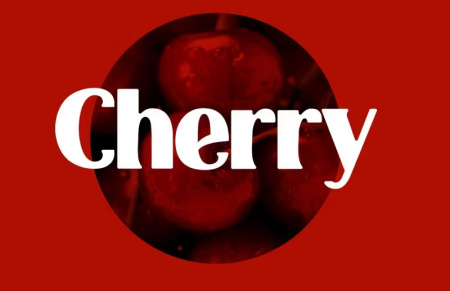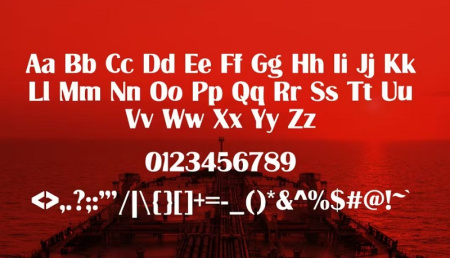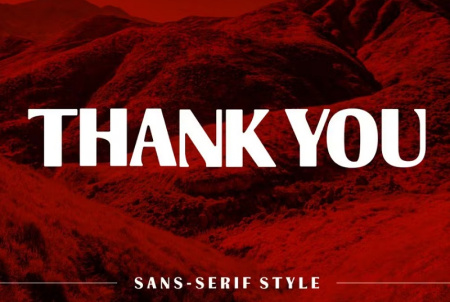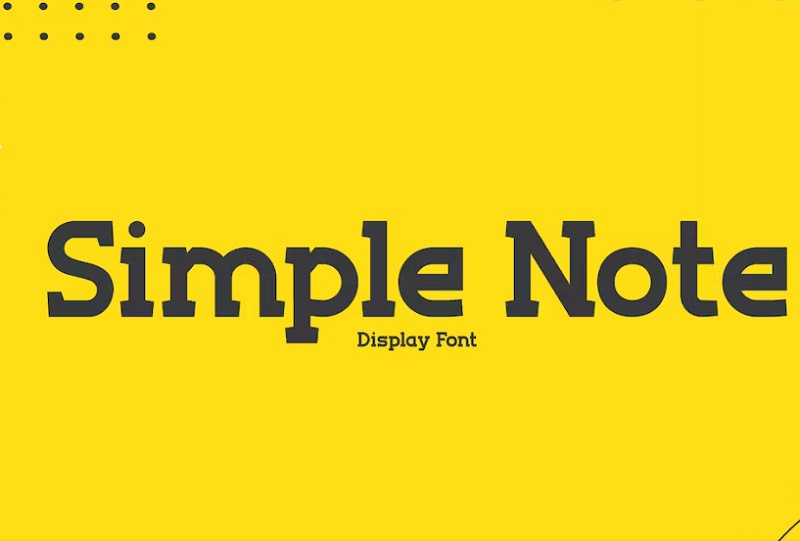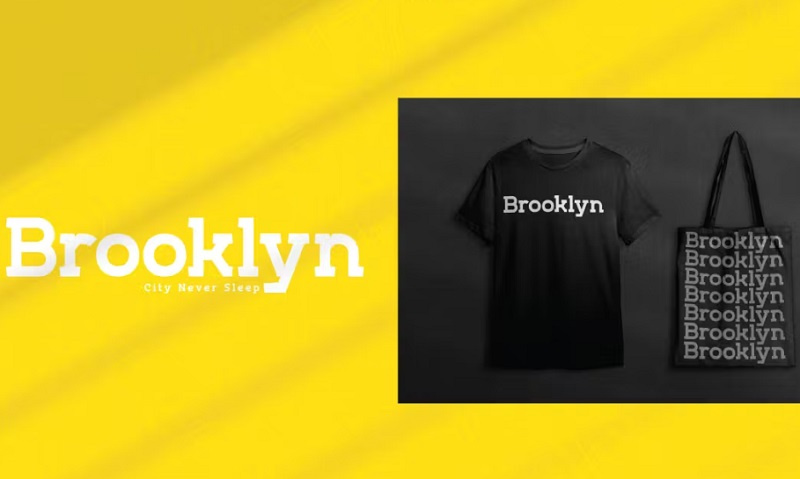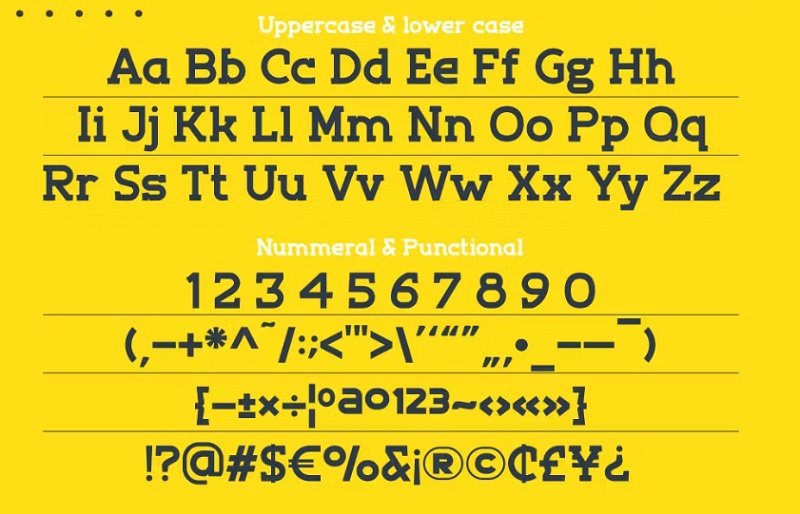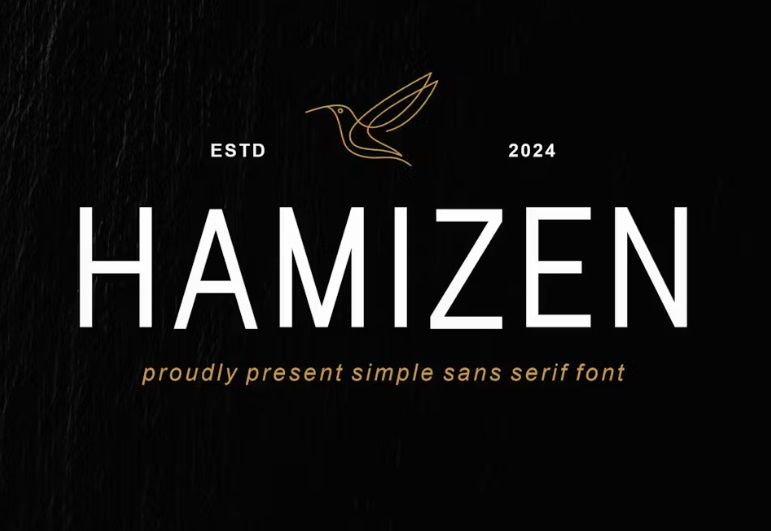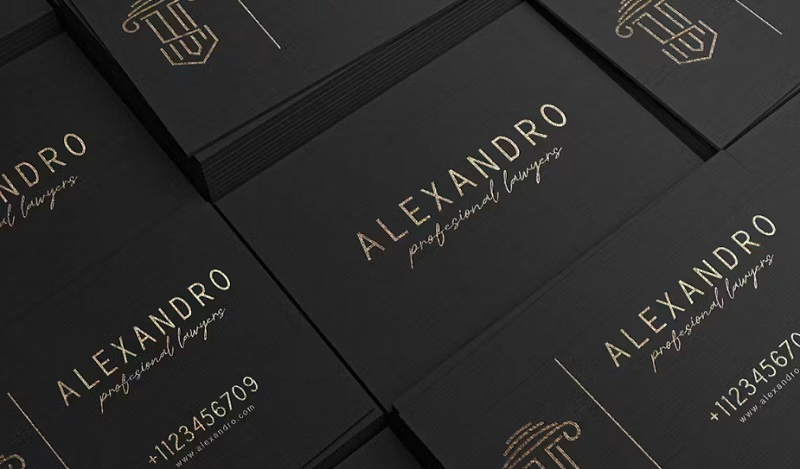
دانلود فونت انگلیسی ساده simple font برای طراحی و اینشات
فونت انگلیسی ساده Bauposkuye
فونت انگلیسی ساده شامل 3 فونت ساده انگلیسی زیبا می باشد. این فونت حس زیبایی و سادگی خاصی را به طرح های شما می دهد. مناسب برای طراح های گرافیکی، تبلیغاتی، چاپ، لوگو، بسته بندی و ... می باشد. برای مشاهده تصاویر این فونت انگلیسی ساده و شیک در ادامه مطلب با سایت gfx همراه باشید.
دانلود فونت انگلیسی ساده Bauposkuye
دانلود فونت انگلیسی Bauposkuye
فونت انگلیسی Bauposkuye
فونت انگلیسی ساده و زیبا Simple Note
2- فونت انگلیسی ساده و زیبا Simple Note
این فونت انگلیسی ساده Simple Note برای برندسازی لوگو، طراحی سرمقاله، مد، داستان های ماجراجویی، طراحی لوازم التحریر، طراحی ورزشی، طراحی وبلاگ، طراحی تبلیغات مدرن، کارت های دعوت، لوگو ها، نقل قول های هنری، دکوراسیون منزل، عنوان/ جلد کتاب، رویدادهای خاص و بسیاری موارد دیگر مناسب می باشد.
فونت انگلیسی ساده و شیک Simple Note
فونتهای انگلیسی ساده Simple Note
فونت انگلیسی ساده برای طراحی
3- فونت انگلیسی ساده برای طراحی Hamizen
این فونت انگلیسی ساده برای طراحی یک فونت مدرن sans serif با سبک زیبا می باشد. این فونت برای برندسازی، لوگو، دعوت نامه، مجلات، بسته بندی محصولات و موارد دیگر عالی است. شامل فایل های OTF - TTF و WOFF می باشد.
بهترین فونت انگلیسی ساده
دانلود فونت انگلیسی ساده و مدرن Bauposkuye
✅ نام فونت انگلیسی: Bauposkuye
✅ نام فونت انگلیسی 2: Simple Note
✅ نام فونت انگلیسی 3: Hamizen - Simple & Modern